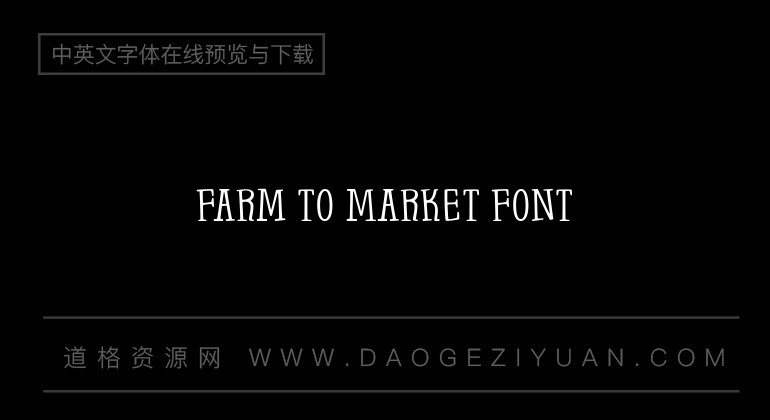
Farm to Market Font是一种受农村和农场风格启发的字体。该字体是由来自美国得克萨斯州奥斯汀的设计师Lauren Ashpole创造的,以展现农村生活的纯朴和自然的感觉。 Farm to Market Font有两个版本:正常的版本和粗体版本。 它的设计受到美国传统手写字体的启发,同时也融入了现代设计的元素。该字体在广告,包装设计,标志设计和其他设计领域中都有广泛应用。它的古朴和舒适感使它在希望传达温暖和自然感觉的设计中非常受欢迎。内容介绍
Farm to Market Font是一款非常不错的手写艺术字体,具有很好的视觉感,适合于文化类的宣传设计、商业类品牌的广告和产品包装设计以及个性化文字排版等较多场景。